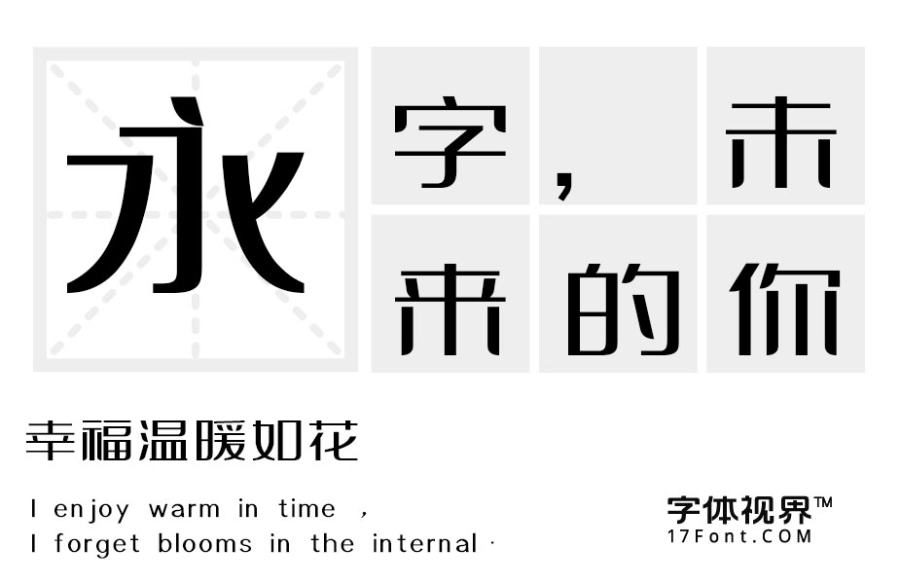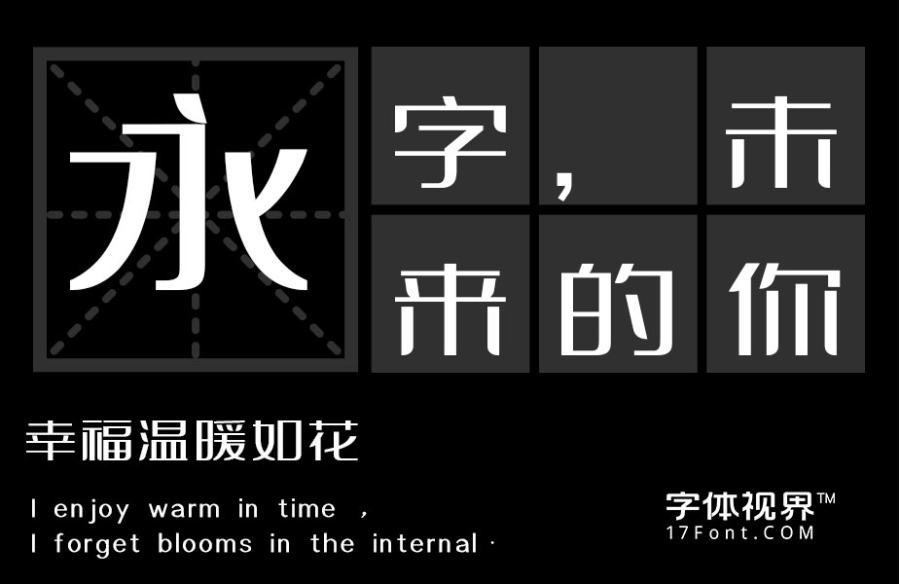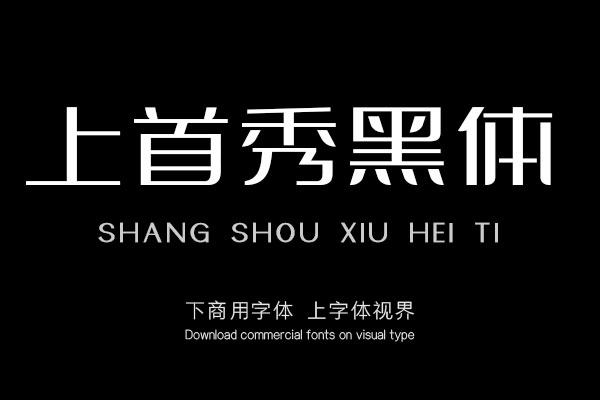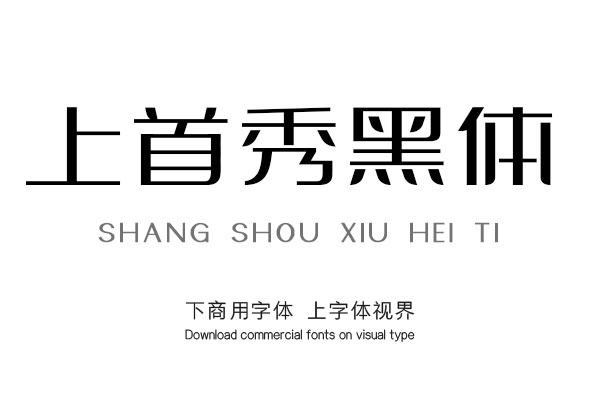
上首秀黑体,整体特征方正稳重,笔画方中带圆。字体右下角转角处作圆角处理,整体结构刚中带柔,干净洒脱,同时洋溢着成熟、稳重、又不缺泛严谨的风格,适用于户外广告、标......购买须知:“下载服务费”与“字体VIP”所获得字体 仅用于个人非商用, 商用请联系付费授权。本字体为电脑用字,手机没有root权限不支持直接手机换字(手机如何root,请自行百度搜索教程)。购买前请先 了解清楚后再付款 ,字体为虚拟产品无法回收 一旦购买不支持退款。